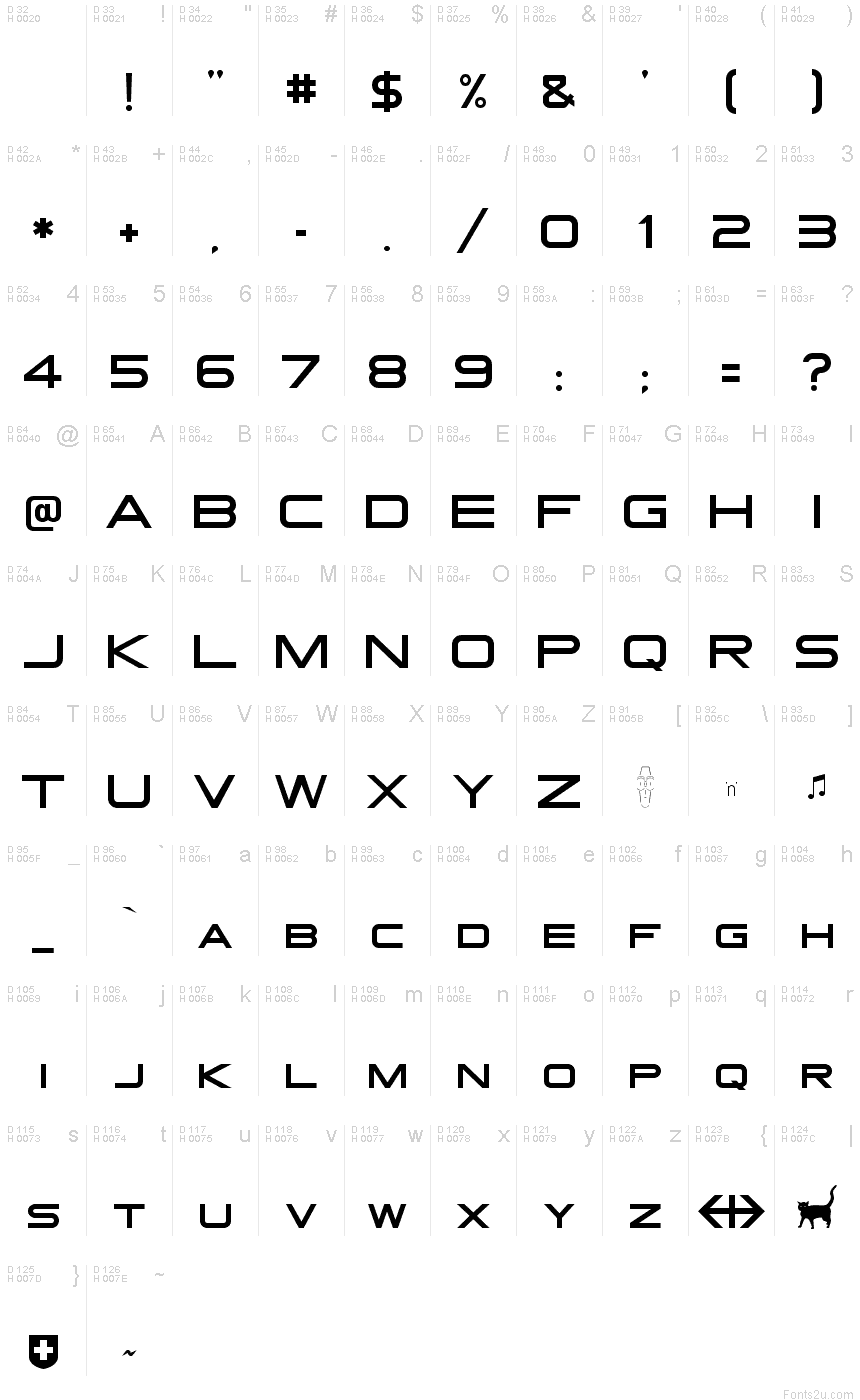
Il font Gotthard di Benn Coifman è un carattere sans serif futurista gratuito. Le sue lettere, costruite con curve squadrate e tratti decisi, danno l'idea di essere state lavorate dal metallo, conferendo al testo una precisione ingegneristica. Gli angoli arrotondati smorzano la freddezza, offrendo uno stile sci-fi tecnologico che resta leggibile e accogliente.
Con Gotthard, titoli e loghi acquisiscono un ritmo modulare serrato, ideale per loghi di gaming, poster di eventi, prodotti tech, interfacce UI, copertine di libri sci-fi e grafiche synthwave. Questo font gratuito dà il meglio di sé con una spaziatura leggermente aumentata e abbinato a un font sans serif semplice per il testo principale.